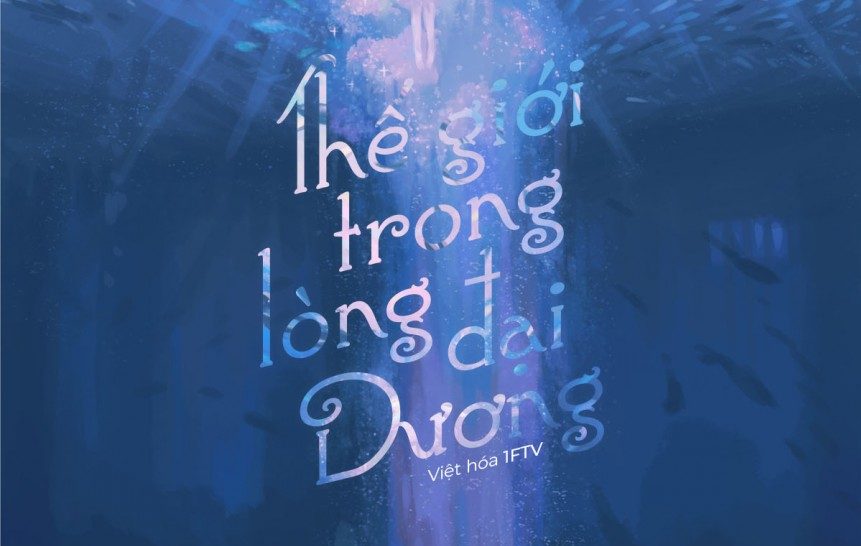
Font việt hóa 1FTV Connie
Trong thế giới đồ họa hiện nay, việc lựa chọn một bộ Font Miễn Phí chất lượng là yếu tố then chốt giúp bài thuyết trình hay tài liệu học tập trở nên lôi cuốn. Font việt hóa 1FTV Connie nổi lên như một lựa chọn hoàn hảo nhờ sự kết hợp tinh tế giữa nét chữ hiện đại và sự mềm mại đặc trưng. Đây là bộ font được tinh chỉnh kỹ lưỡng về dấu tiếng Việt, giúp các bạn học sinh và thầy cô dễ dàng sử dụng trong mọi ngữ cảnh giáo dục mà không lo lỗi hiển thị.
Ưu điểm nổi bật của Font việt hóa 1FTV Connie
Thiết kế hiện đại và dễ đọc
Bộ Font việt hóa 1FTV Connie sở hữu các đường nét thanh mảnh nhưng vẫn giữ được độ dày vừa phải, tạo cảm giác chuyên nghiệp và gọn gàng. Cấu trúc chữ cái được tối ưu hóa để tăng khả năng nhận diện, giúp người xem không bị mỏi mắt khi đọc các đoạn văn bản dài trên slide bài giảng hoặc báo cáo khoa học.
Khả năng ứng dụng đa dạng trong học tập
Không chỉ dùng cho tiêu đề, Font việt hóa 1FTV Connie còn phát huy tác dụng tốt trong thiết kế thiệp mời, bìa sách và các ấn phẩm truyền thông của câu lạc bộ trường học. Sự linh hoạt này giúp người dùng tự do sáng tạo mà vẫn đảm bảo tính thẩm mỹ cao cấp nhất.
Lưu ý khi sử dụng Font việt hóa 1FTV Connie
Khi sử dụng bộ font này, bạn nên kết hợp với các tông màu trung tính để làm nổi bật sự thanh lịch của nét chữ. Ngoài ra, việc điều chỉnh khoảng cách dòng hợp lý sẽ giúp bố cục thiết kế trở nên thông thoáng và dễ nhìn hơn. Đây thực sự là công cụ đắc lực cho những ai yêu thích sự tối giản nhưng vẫn muốn tạo dấu ấn riêng biệt.
Kết luận về bộ font chất lượng